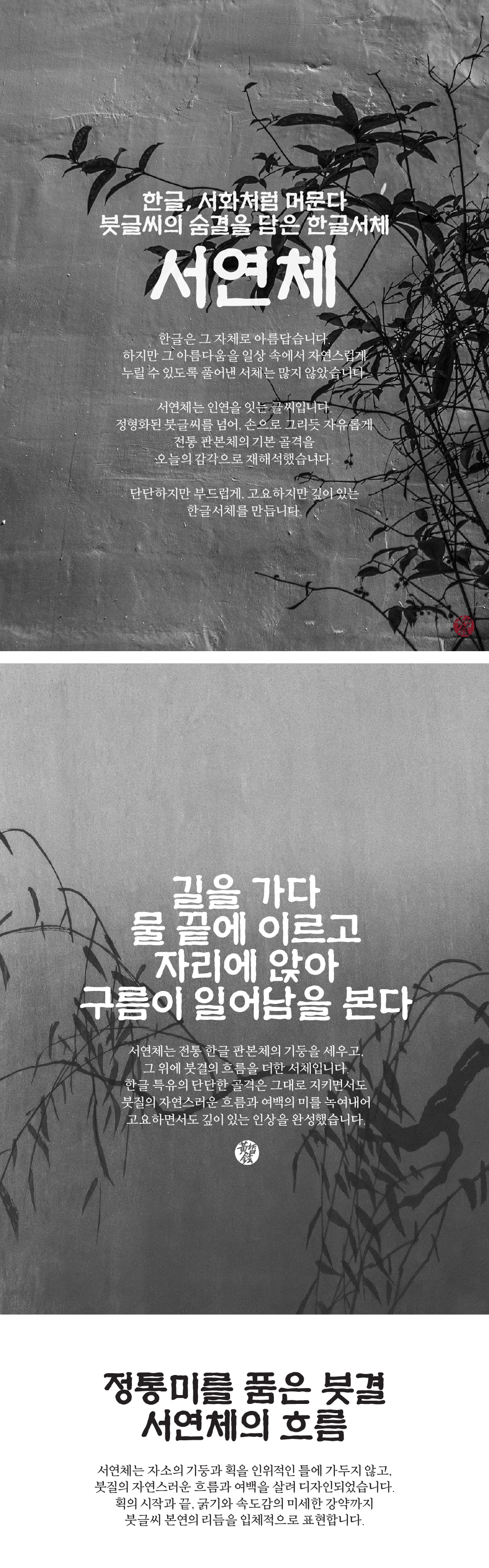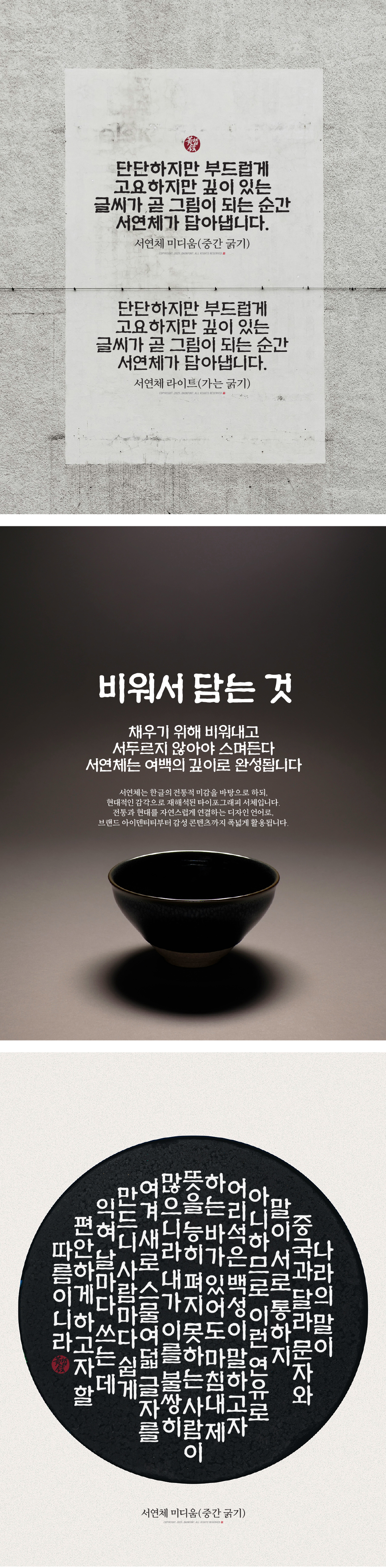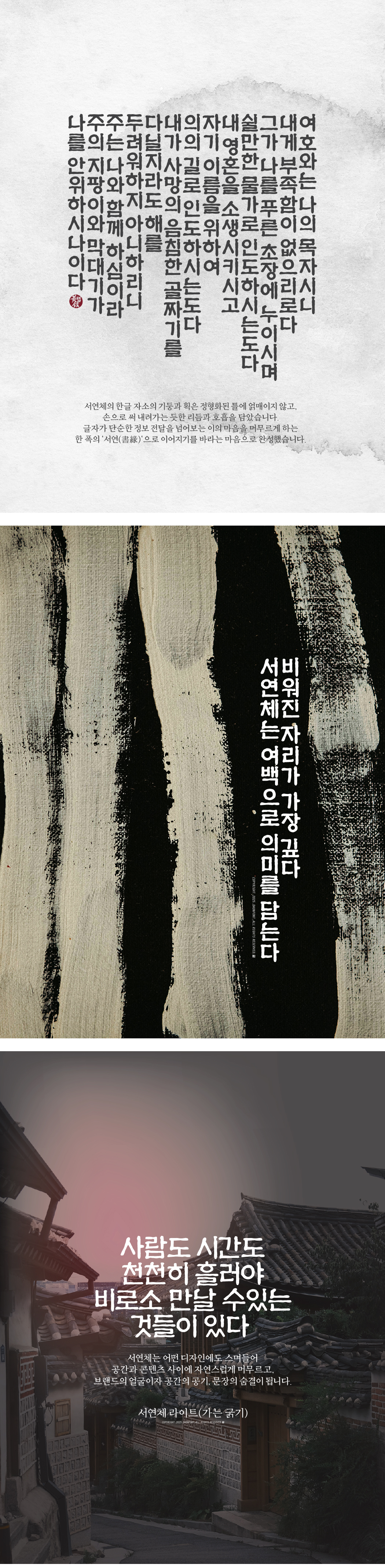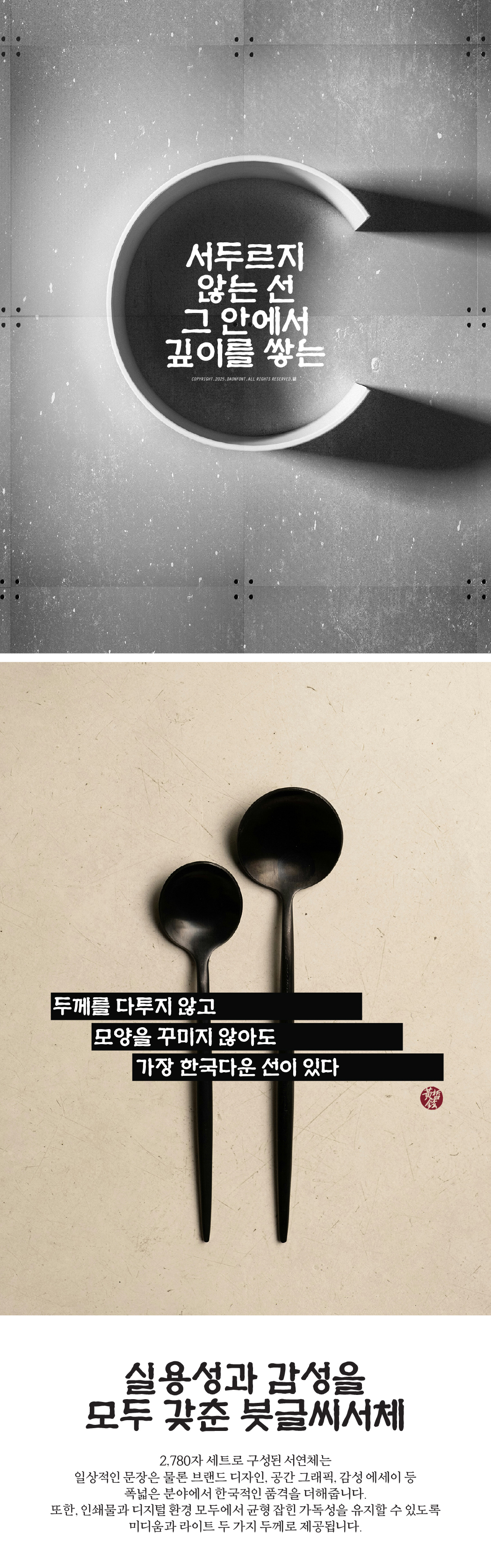
다온폰트 6월 신규폰트 "서연체" 출시
6월 13일 다온폰트 신규폰트 "서연체"가 출시 되었습니다.
서연체는 전통 판본체의 견고한 골격을 바탕으로 디지털 환경에서도 높은 가독성을 구현했습니다.
정밀한 세로 장평과 균형 잡힌 글자폭으로 문장이 흐를 때 가장 자연스럽고 안정적인 조형을 유지하는 서체입니다.